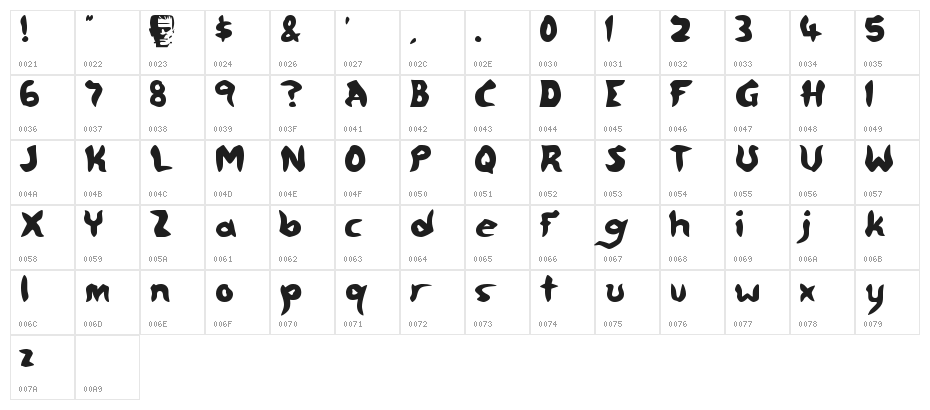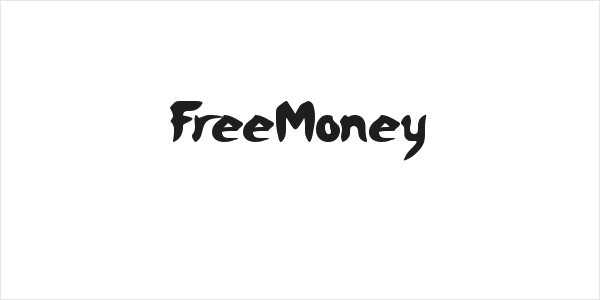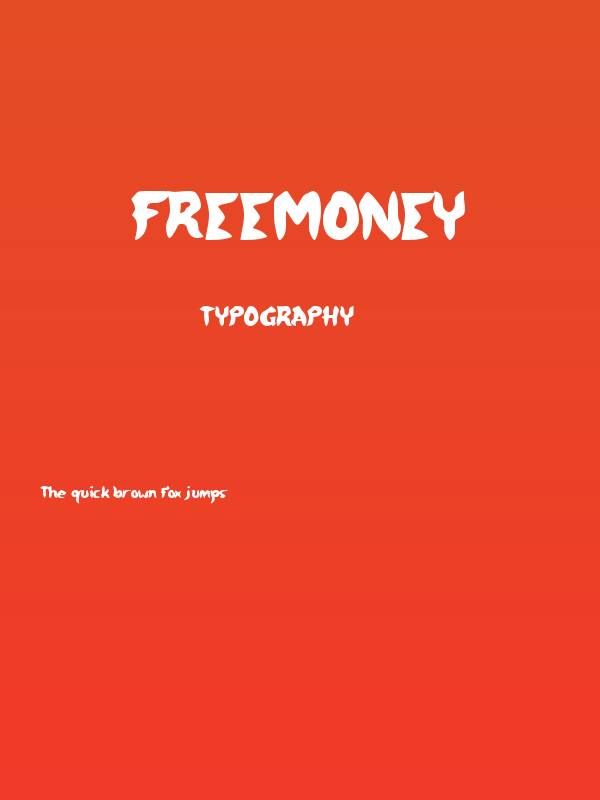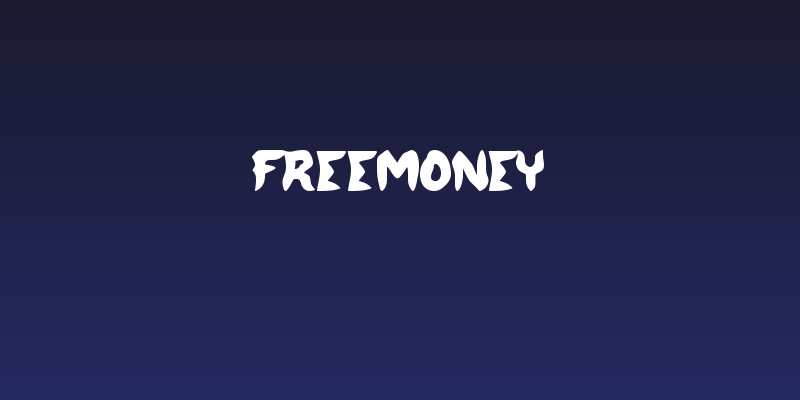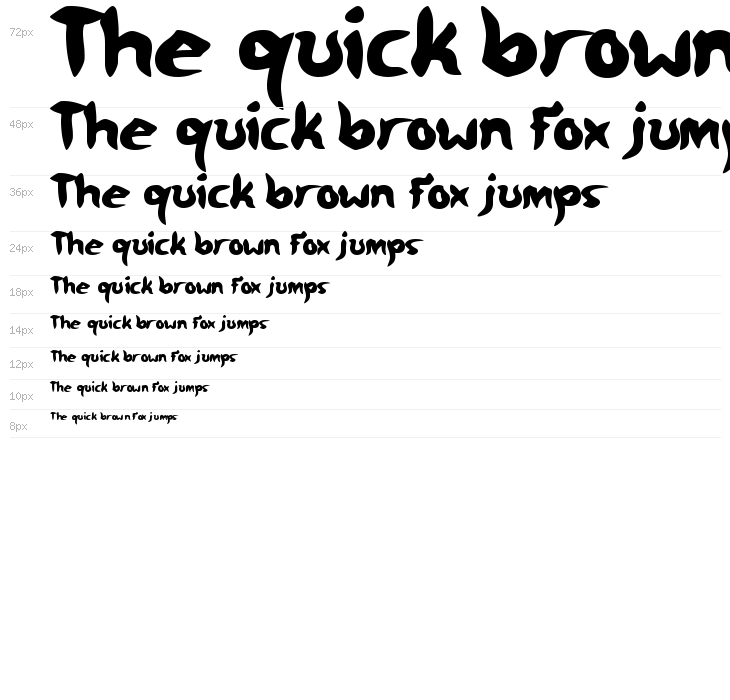
FreeMoney Font
✎ Comic
| Nome | FreeMoney |
| Categorie | Comic |
| Stile generale | Playful and Energetic |
| Caso d'uso | Headlines, Posters, Creative Branding |
| Progetti proposti | Ideal for posters, children's books, comic strips, and creative branding. |